「黒龍爽」に似ているおすすめ日本語フリーフォント
今回は、昭和書体から発売されAdobeFontsでも提供されている「黒龍爽」フォントに似た雰囲気やスタイルをもつフリーフォントをご紹介します。
アニメ「鬼滅の刃」で使われていることで、一躍人気になったフォントです。フォントイメージは、暗雲立ち込める空を荒々しく漂うさまをイメージして作られた筆書系デザイン書体、販売されてからとっても人気がある筆フォントの1つです。
今回は、そんな「黒龍爽」に似た雰囲気をもつ日本語フリーフォントをまとめてみました。
「黒龍爽」に似た雰囲気があるフリーフォント
フォントを選ぶ際の参考になればと思い「いいフォント」運営者が主観で似た雰囲気やスタイルがあると感じたフォントを選定しています。
「黒龍爽」と全く同じフォントというのはなかなかありませんが、自分が求めている印象に近いものを探してみてくださいね。
筆の動きが躍動的、で力強さを感じられるとてもステキなフォントです。
玉ねぎ楷書
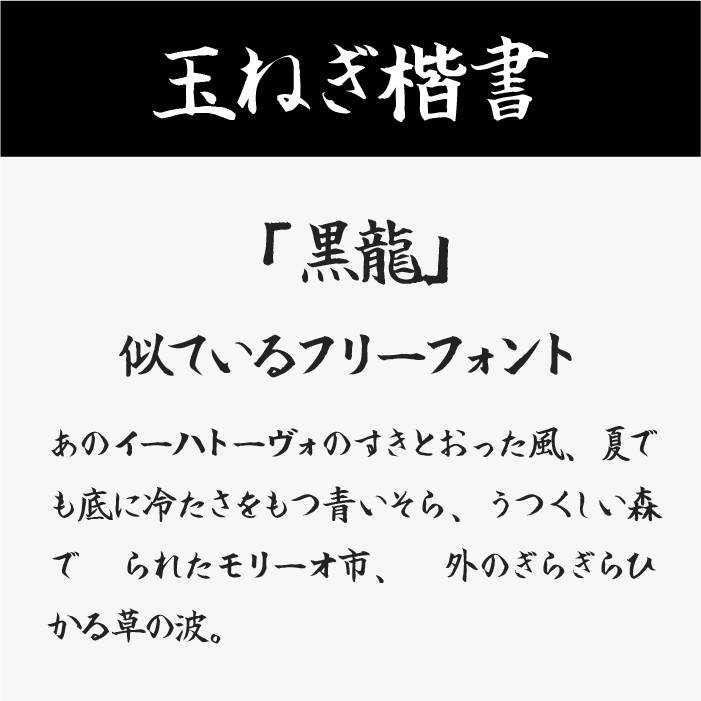
玉ねぎ楷書フォントは、柔らかな線と落ち着いた筆致が心地よい、スタンダードな筆文字フォントです。
やや控えめな墨の質感と、整った字形が読みやすく、黒龍爽の荒々しさを少し抑えた表現にしたいときに活用できます。力強さと品の良さを両立したいデザインにも適しています。
玉ねぎ楷書激
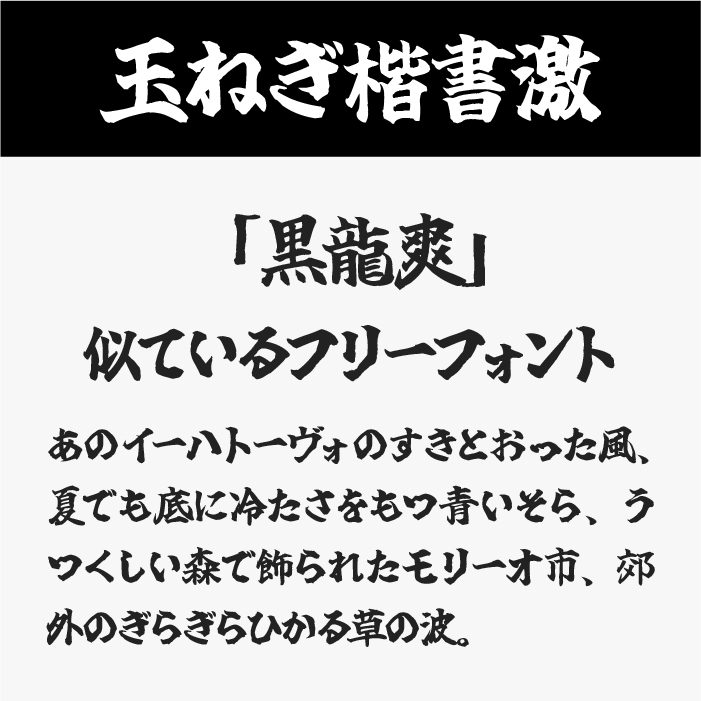
玉ねぎ楷書激フォントは、筆の跳ねや力強い抑揚が魅力の、ダイナミックな書体です。
太めのストロークと緻密な造形で、目を引く強さと読ませる迫力を兼ね備えています。黒龍爽のような重厚さやスピード感のあるタイトルと親和性が高く、インパクトを出したい場面にぴったりです。
達筆(笑)フォント
遁筆(笑)フォントは、ラフな崩しと軽妙な動きが特徴の、ユニークな手書きフォントです。
一文字ごとの揺れや傾きが独特で、躍動感のある見た目に仕上がります。黒龍爽の持つ野性味や、荒々しさの演出にもぴったりです。
しょかきうたげ
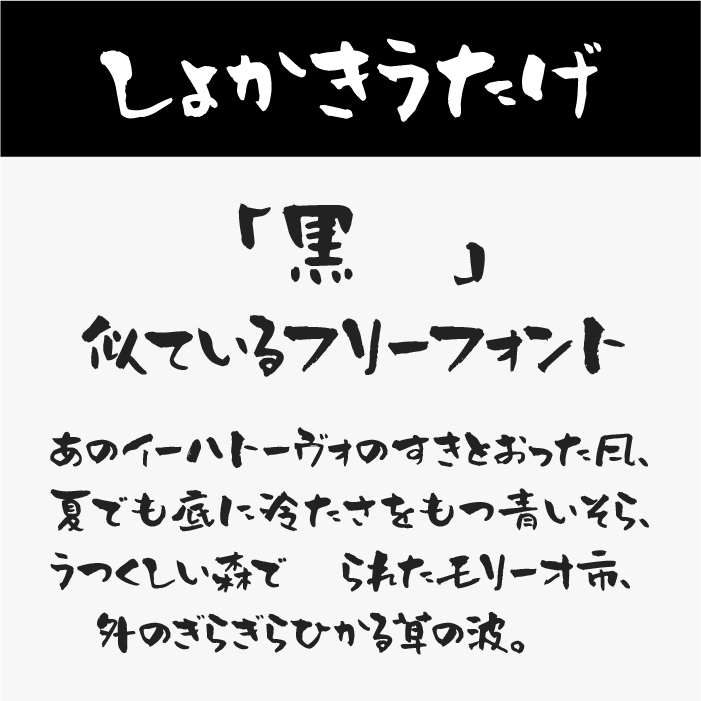
しょかきうたげフォントは、墨のにじみや手書きらしさがにじむ、奔放な筆文字フォントです。
線の丸みと不均等なリズムがどこか親しみやすく、荒さの中にも軽やかさがあります。黒龍爽のような硬派で重みのある書体に、少し柔らかみを加えたいときにおすすめです。
勇獅子フォント
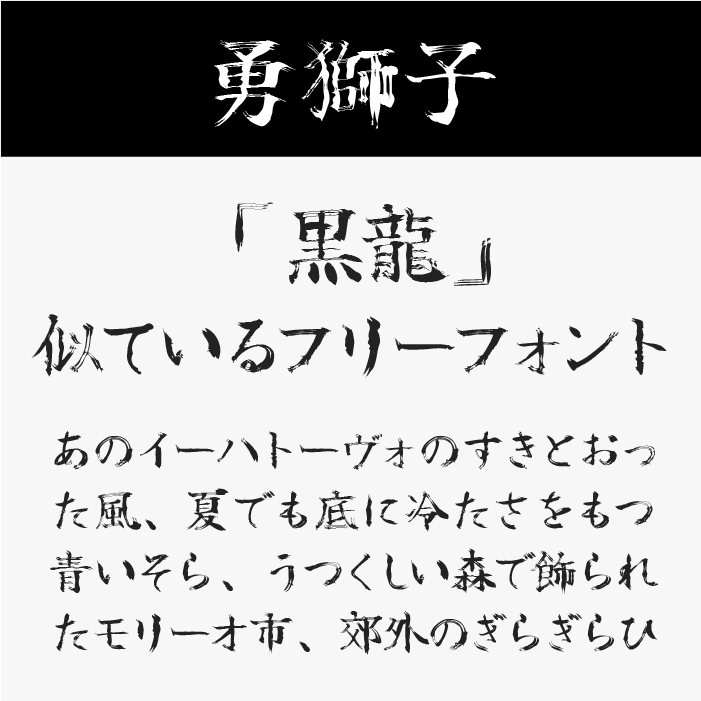
勇獅子フォントは、筆のかすれや荒々しさが際立つ、野性味あふれるフォントです。
線の太さや勢いのある筆致が、力強い印象を与え、手書きのラフさと重厚感が合わさっており、「黒龍爽」が持つ鋭さや緊張感をうまく引き出すのに適したフォントです。
不知火
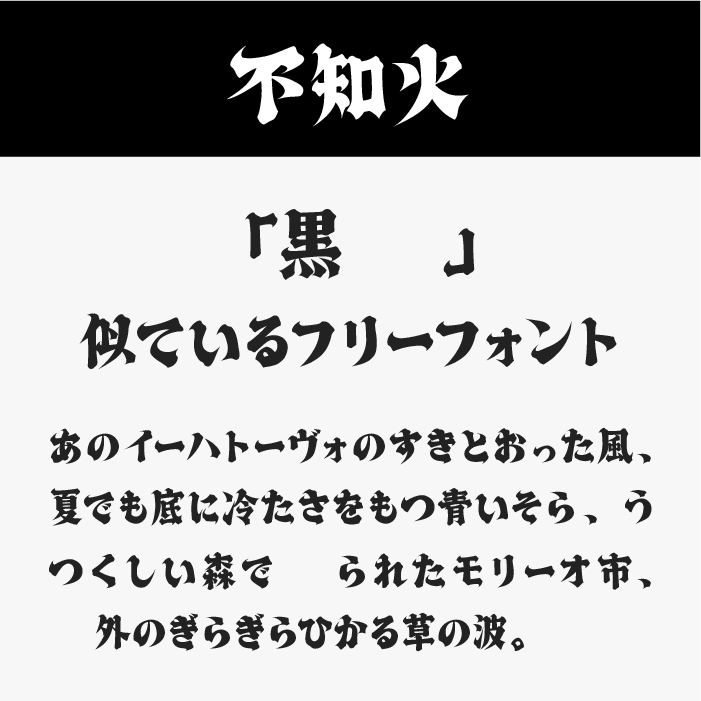
不知火フォントは、骨太でキレのある造形が印象的な、武骨さを感じさせる筆文字フォントです。
エッジの効いた文字形と均整の取れたバランス感で、黒龍爽と同様に、緊張感や凛とした空気をまとったビジュアルを作りたい場面にぴったりなフォントです。